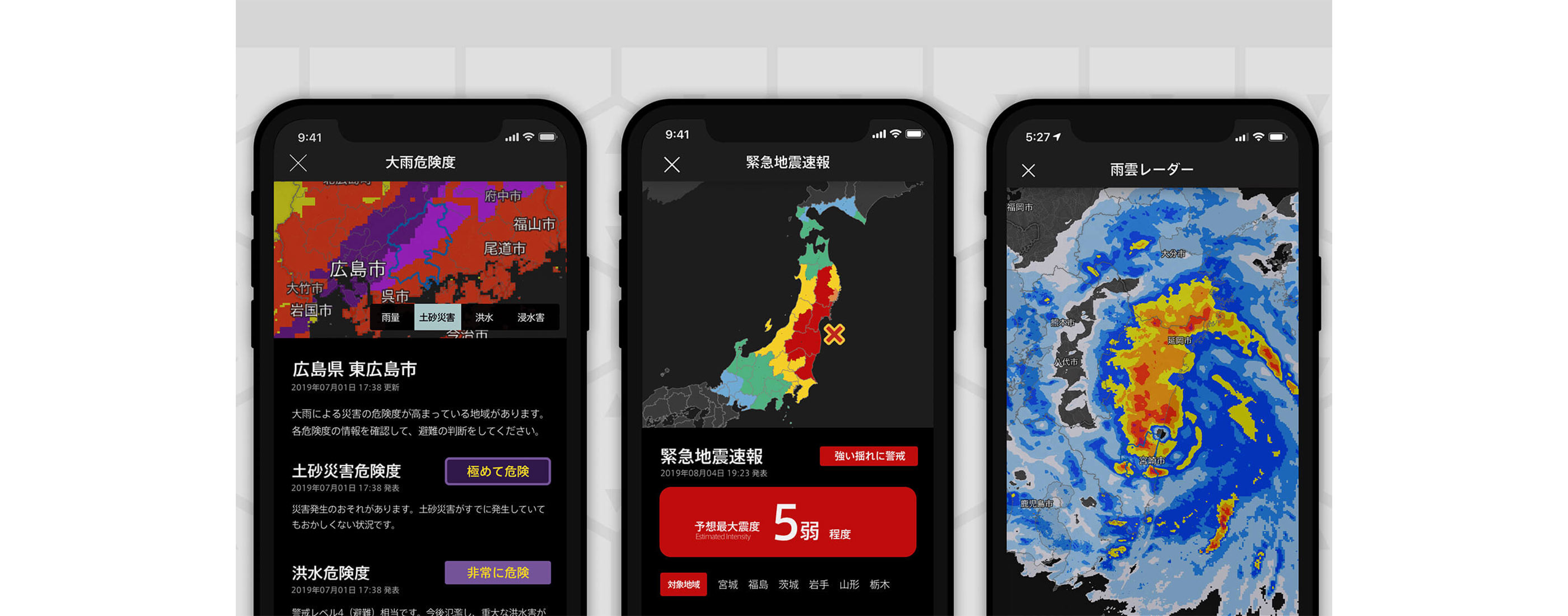
視認性で選んだベストなフォント
ゲヒルン株式会社は、安全保障を軸に「インフラストラクチャ」「情報セキュリティ」「防災気象情報配信」の3つの分野でサービスを提供するセキュリティ会社です。情報セキュリティでは、検査対象に合わせた擬似攻撃を実施し、システムの脆弱性や、開発者が想定していない挙動や問題を見つけ出し、課題の改善案を提出します。防災気象情報配信では、天気や台風の予報、地震・津波の速報や特別警報などのさまざまな防災情報を、ひとつのアプリケーションで提供するサービス「特務機関NERV(ネルフ)防災」の提供を開始しました。発売から1ヶ月で 27万ダウンロードを記録した「特務機関NERV防災」では、AXIS Fontが採用されています。また、ゲヒルンでは、コーポレートフォントとしてAXIS Fontを採用し、名刺やパンフレット、作画エンジンで使用しています。
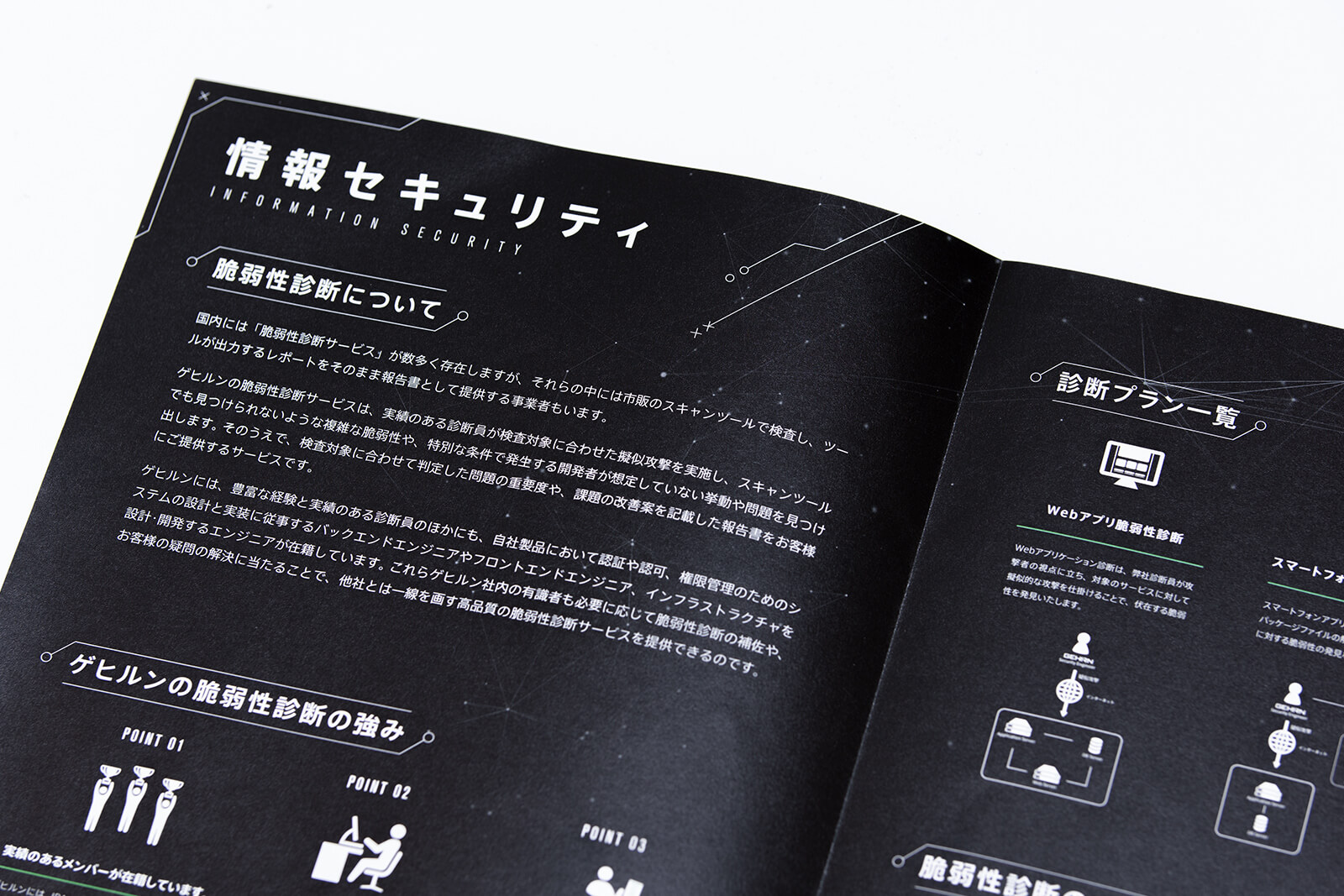
「AXIS Fontには一目惚れだったので、会社設立の時に迷わずコーポレートフォントにしました。『特務機関NERV防災』に採用するフォントを決める際には、他のいくつかのフォントも検討しましたが、表現したいイメージと違っていました。デザイナーや開発チームからも要望が出て、やはりAXIS Fontが一番良いということになりました。」と、ゲヒルン株式会社 代表取締役 石森 大貴氏は述べています。
ゲヒルンでは、約20名の社員のほぼ全員がデザイナーかエンジニアで、開発はすべて内製しています。アプリケーションのデザインとUI/UXを担当する専務取締役 糠谷 崇志氏は、「私たちの事業は、自分たちが最初のユーザーだと思っています。だから、自分たちが納得するものしか世に出したくない。情報セキュリティでは自分たちが受け取りたいと思う報告書、防災気象情報配信では自分たちが使いたいと思うアプリを作りたい。『ユーザー視点を大切に』というところに一番強い思いがあります。作画エンジンで見慣れていたのもありますが、他のフォントではしっくりこなかったので、防災アプリでは初めて目にしたときからずっと好きなAXIS Fontを採用したいと思いました。」と語ります。
特務機関NERV 防災アプリは、地震や津波、特別警報や土砂災害といった防災気象情報を、被害が予想される地域で的確に認識できるように、気象庁と連携して国内最速レベルで配信するスマートフォン用サービスです。ゲヒルンでは、既存の防災アプリに対し、情報提供のスピードやユーザービリティ、デザインの部分で優位性があると考え、アプリケーションの開発に着手しました。
「危機管理は、物理の世界でも情報セキュリティでも同じです。情報セキュリティは、事業継続計画のための一部であり、災害対応は外せないリスクファクターですので、情報セキュリティと防災気象情報配信サービスは、繋がっている分野だと思います。2011年の東日本大震災から8年ほど、特務機関NERVという個人のTwitterアカウントで防災情報を配信していました。Twitterの場合、ひとつのアカウントで全国の情報を出すことになります。そこで、地域ごとに詳しい情報を届けるために、プッシュ型で情報を出すことを考え、特務機関NERV防災アプリを開発しました。」(石森氏)
アプリケーションから緊急地震速報をプッシュ通知するためには、気象庁長官から予報業務の許可を受けなければなりません。特定の地域での地震到達予想時刻と、予想される震度を出すための計算式を記述した申請書を1ヶ月かけて作成し、気象業務支援センターから気象庁との専用ラインを引きました。また、マナーモード時でも緊急アラートを鳴らすための重大な通知の契約にも時間がかかったと言います。
「気象庁では、警報が出た際に各自で地域ごとの情報を確認することを期待しているのですが、それが活用されていないというのが現状でした。特務機関NERV防災アプリでは、土砂災害警戒情報がでると1キロメートルごとのメッシュ単位でどこが危ないかがわかります。震度1などTwitterでは細かすぎて出していなかった情報も、アプリでは該当地域だけに表示できるようになりました。」(石森氏)
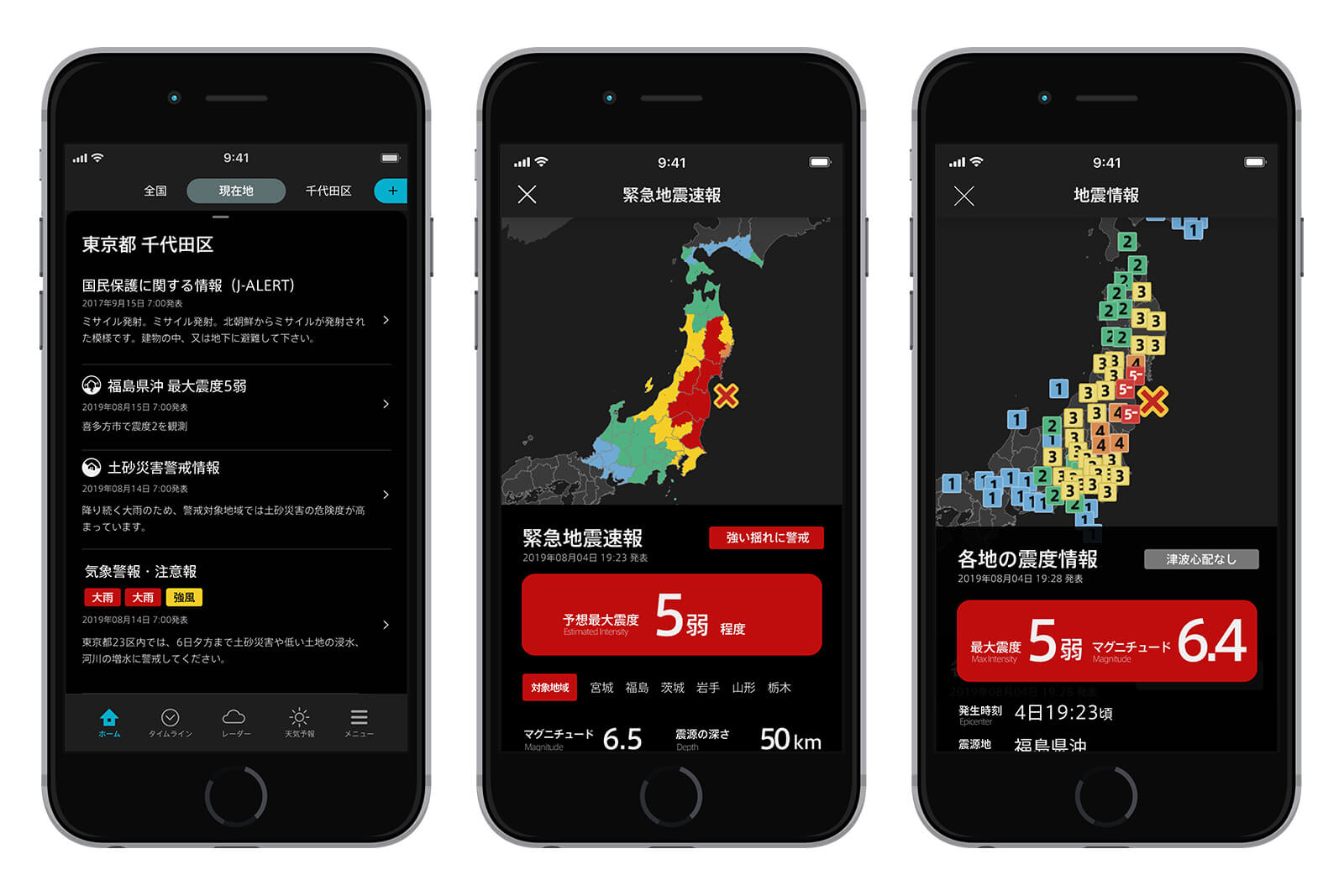
アプリケーションは、「美術的なもの」「技術的なもの」そして「哲学」を含む芸術作品に近いものと捉えるゲヒルンは、特務機関NERV防災アプリに自分たちの哲学を反映していると言います。そのため、デザインのコントロールを優先し、アプリケーションのビジネスモデルとしての広告収入を考えず、ユーザー利用規約にも他社の広告への誘導をしないことを明記しています。
「もっとも危険な場所を濃い紫にするなど、色で自分のいる地域のどこが危ないかを判断できるようにしています。説明がなくても、自然に必要な詳細情報に辿りつくような設計、そこにわれわれの哲学があるのです。」(石森氏)
ドイツ語で「頭脳」という意味を持つゲヒルンは、エヴェンゲリオンに由来しています。エヴェンゲリオンのファンだった石森氏と糠谷氏は、アプリケーション開発の際に、改めて公認の承認を得たことで「特務機関NERV防災」のデザインを変更しました。そのデザインは開発チームが驚くものだったと言います。
「寄せてはいますが、エヴェンゲリオンを前面に出したデザインにはしていません。防災アプリなので、黒を基本として色を控えめにするという基本的な方向性がありました。紫や赤は警告色なので、必要なときだけ出すようにしています。デザインやAXIS Fontに関しては、気象庁とエヴァンゲリオンシリーズの映像企画・製作会社である株式会社カラーからも、とても読みやすいと喜んでもらえました。」(糠谷氏)
特務機関NERV防災アプリのユーザーからも、とても読みやすいという声が多く届いているといいます。「『AXIS Fontだからダウンロードした』というユーザーもいました。AXIS Fontはそこにあるだけで知的な感じがするのと、重心が低いから安定性があります。また、視認性が高いので防災情報を伝えるのにベストなフォントだと思って採用しました。」(石森氏)